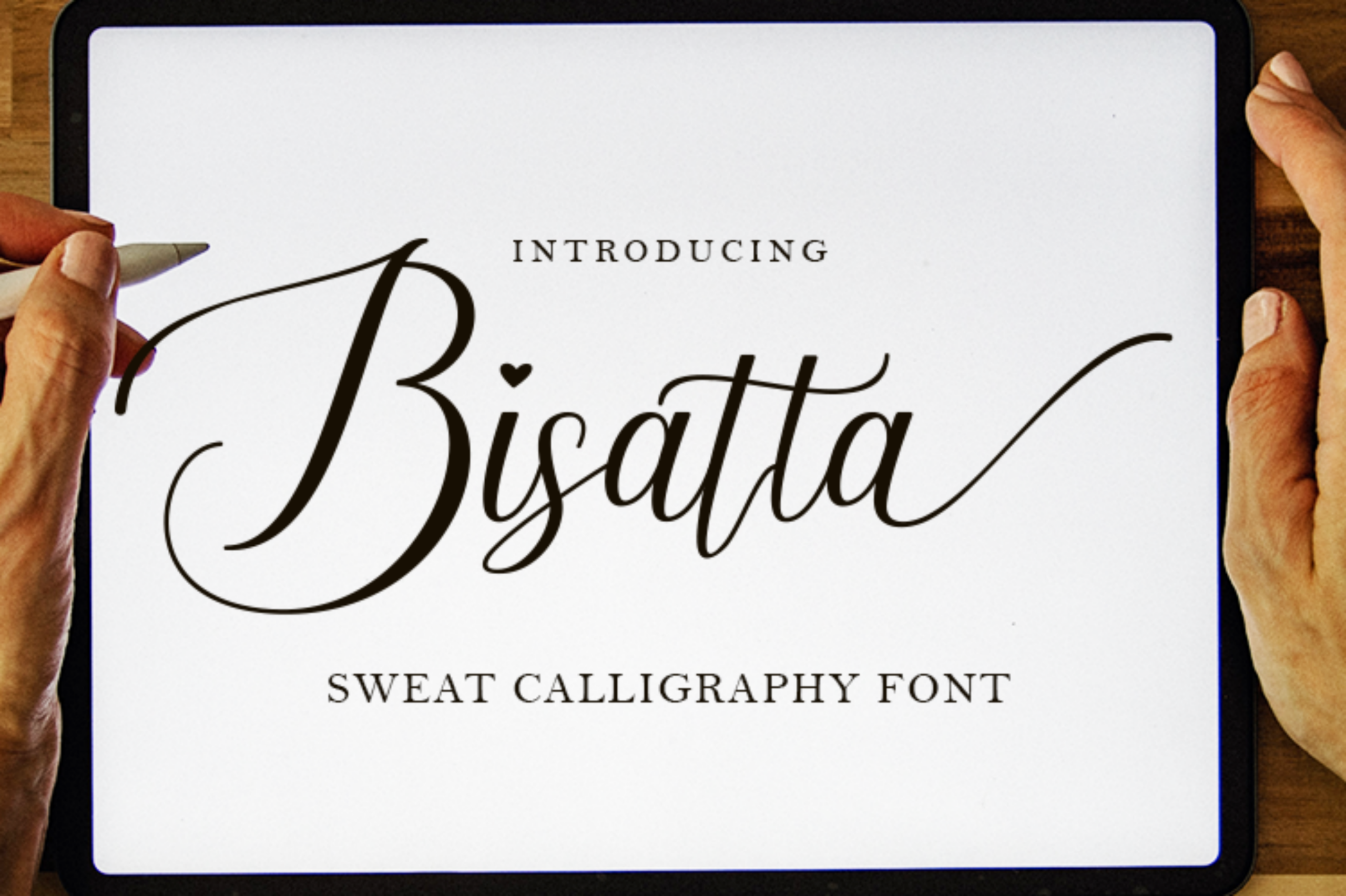
Bisatta Calligraphy Font – Download Grátis
Esta é uma linda e delicada fonte de script que exala elegância e classe. Ideal para quem precisa de um look agradável e renovador em seus designs. Bisatta Calligraphy possui codificação PUA, o que permite que você acesse todas as maravilhosas letras e ligaturas facilmente. Esta é uma fonte criada especialmente para aqueles que desejam tornar seus projetos ainda mais sofisticados e elegantes. Com certeza vai ser um excelente recurso para qualquer designer gráfico ou artista de arte digital procurando por uma fonte única e envolvente.
Designer: yontype